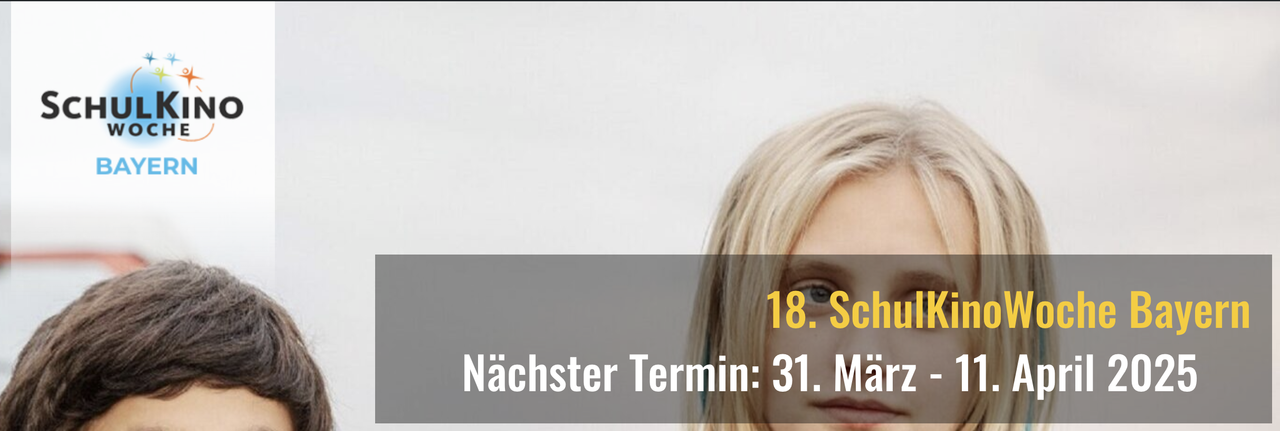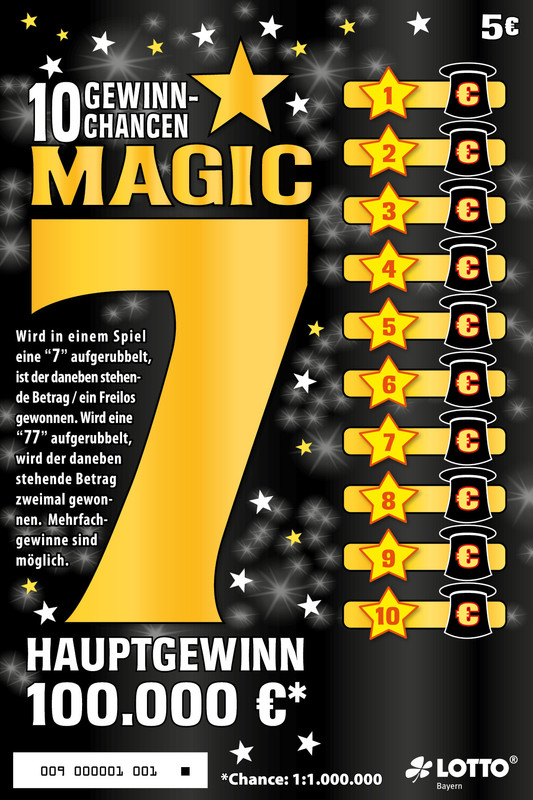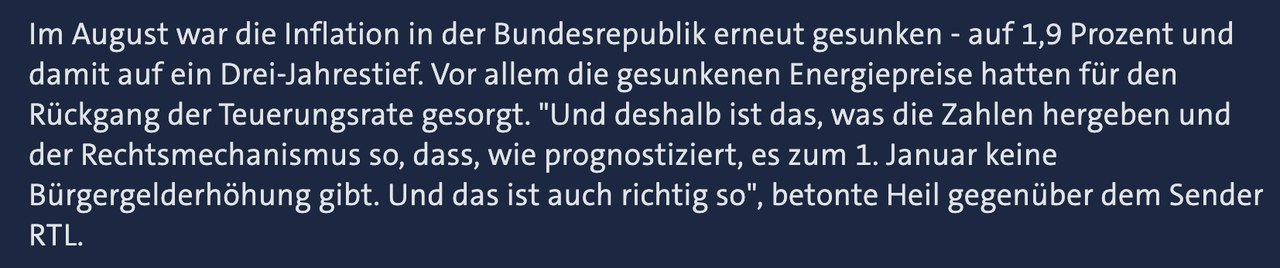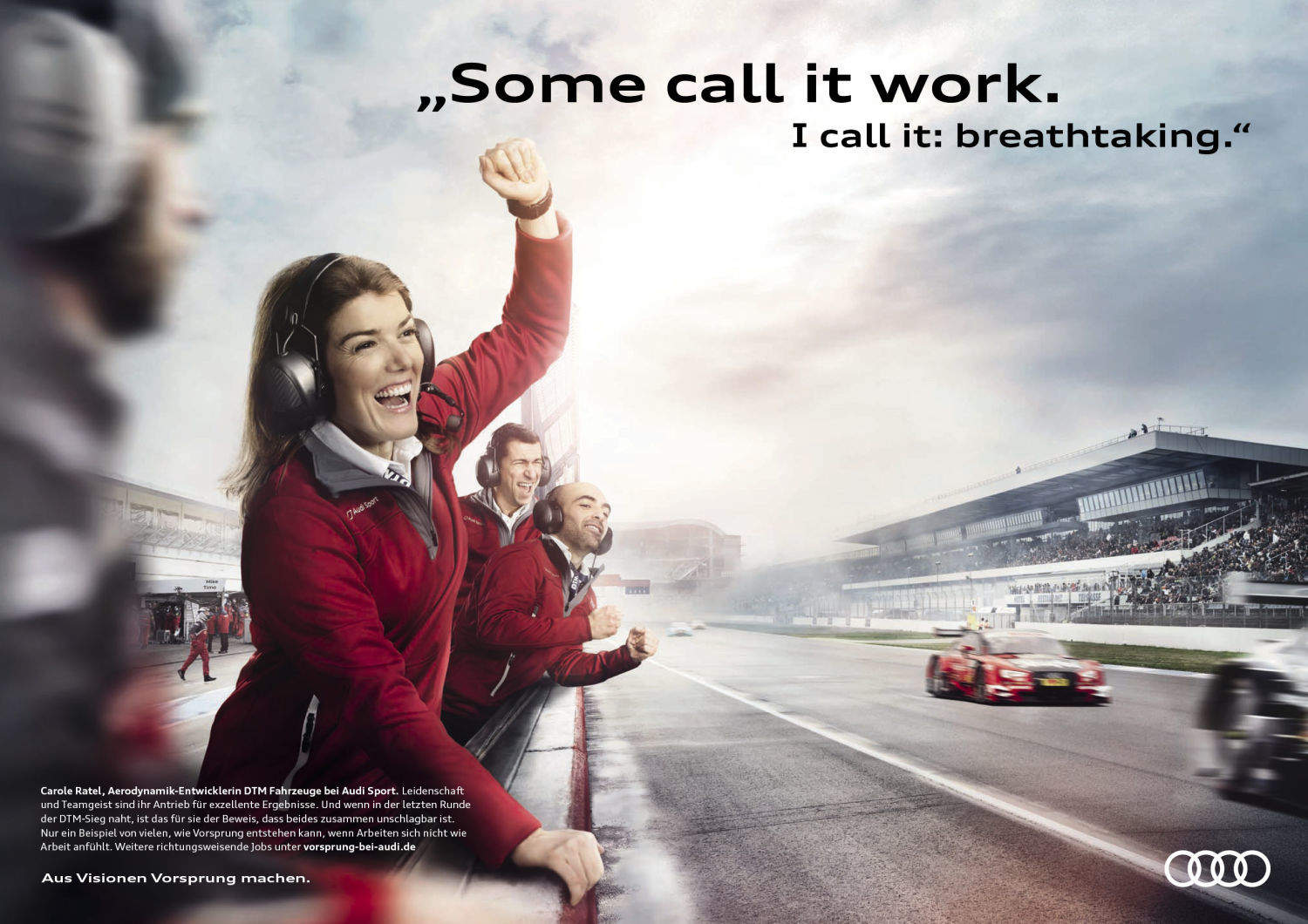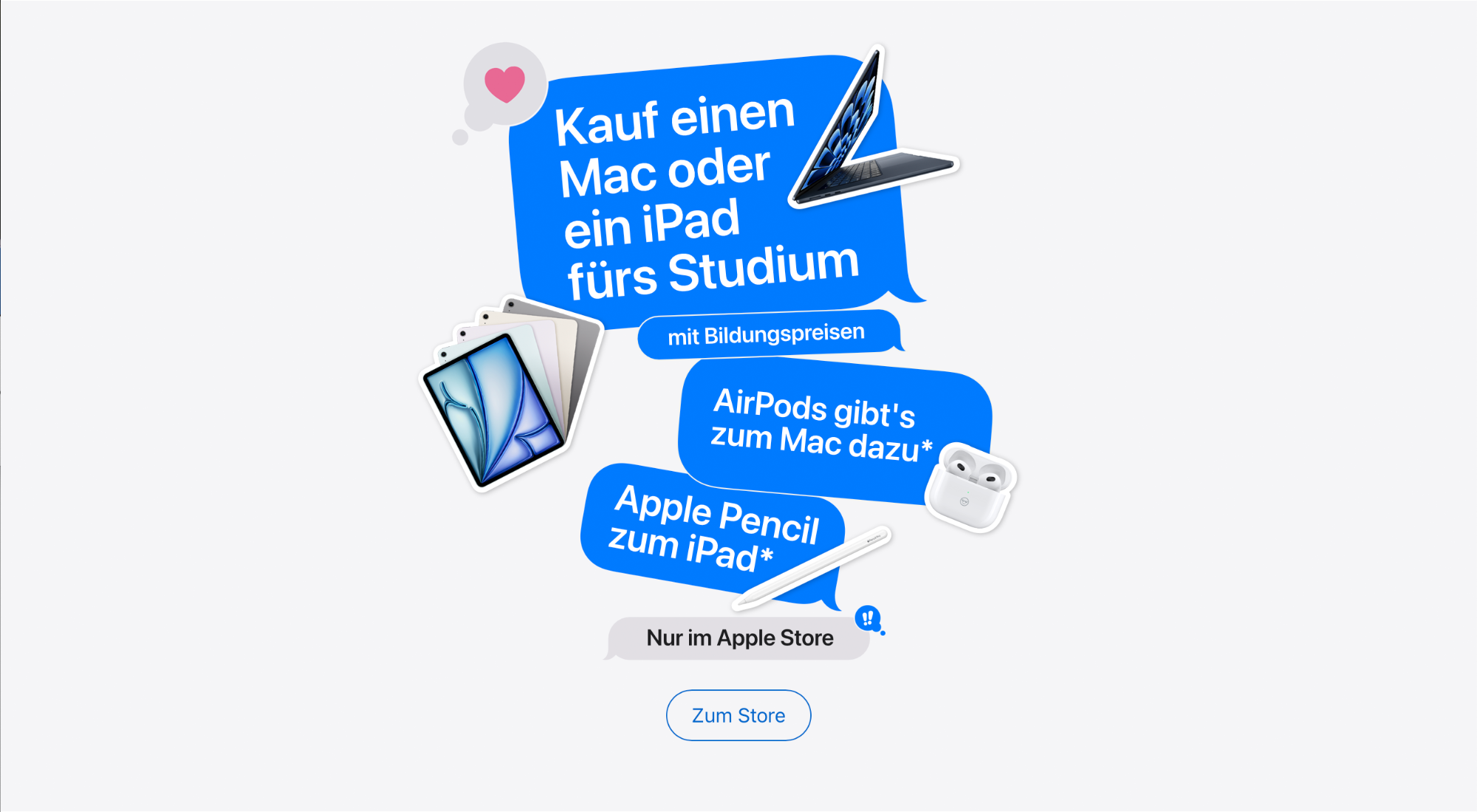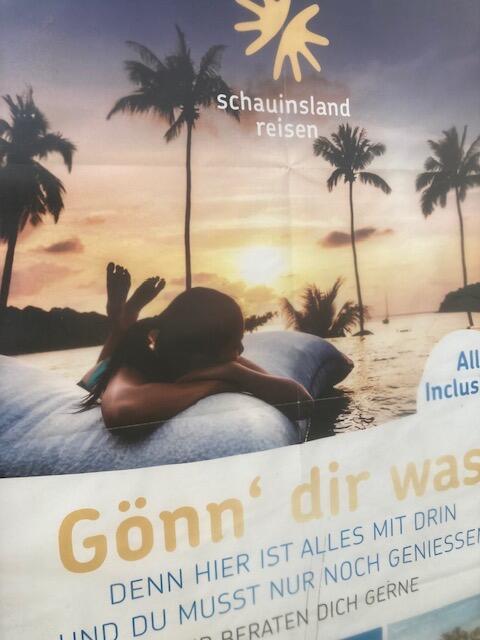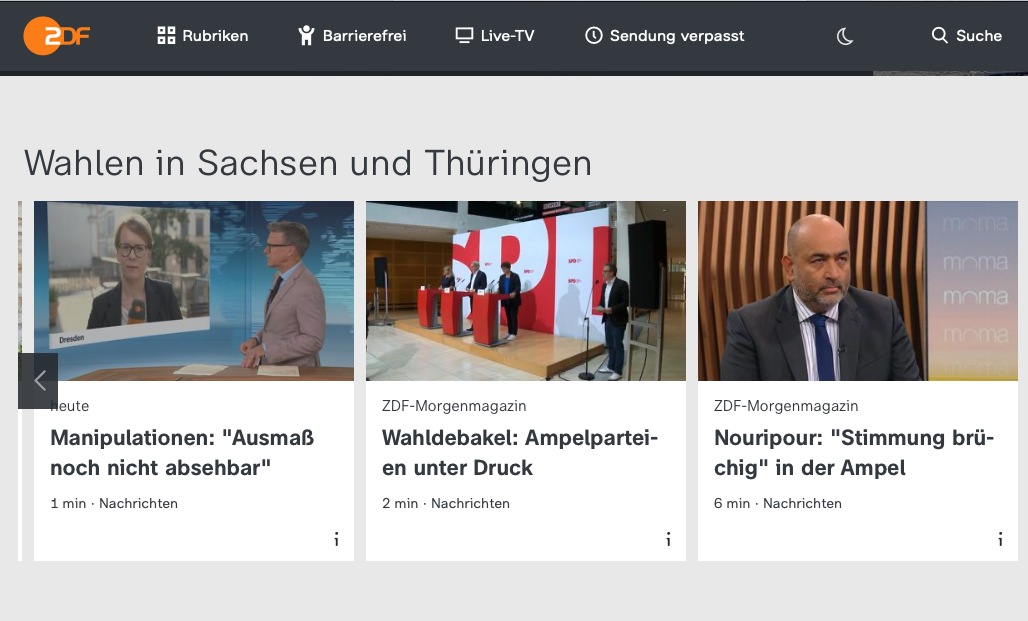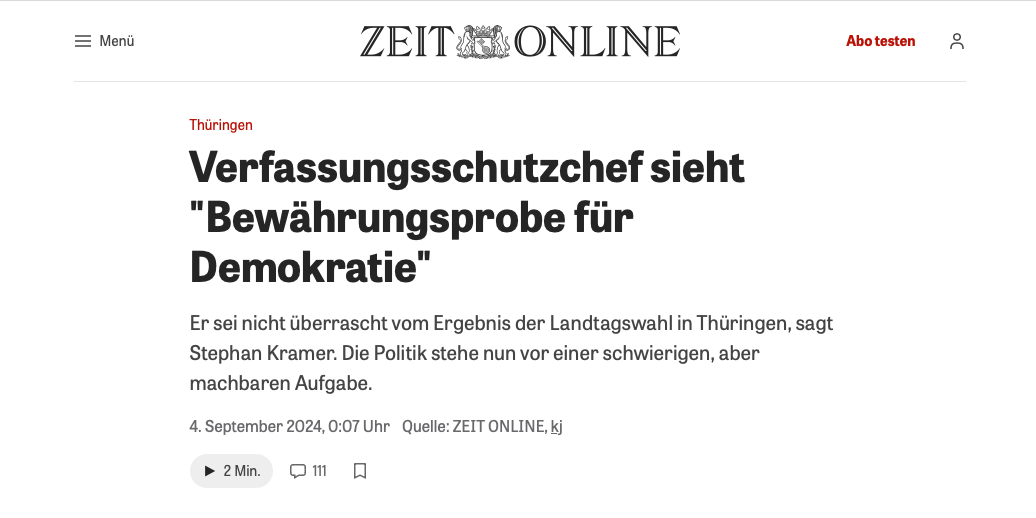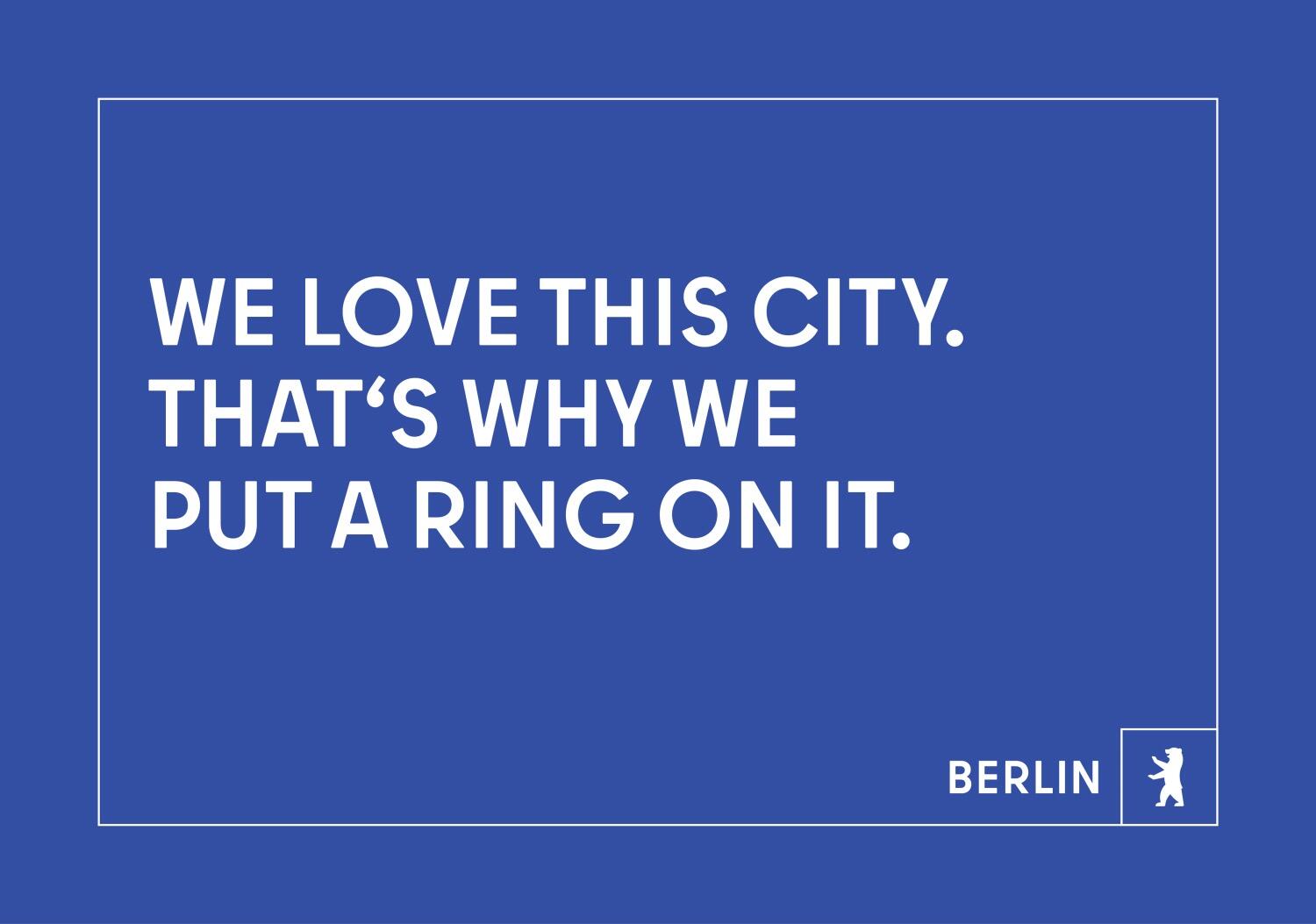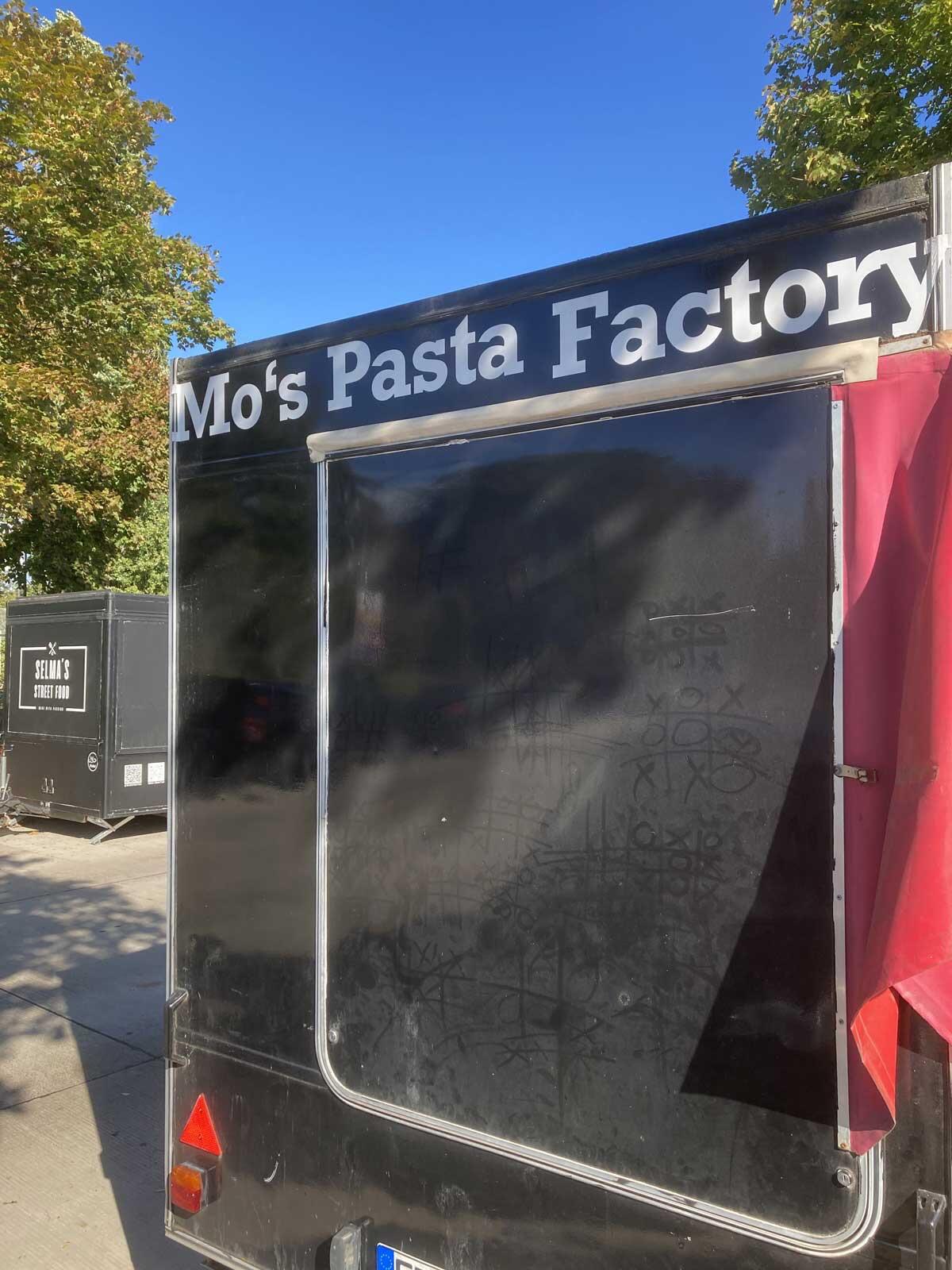
Prominente Beispiele falscher Zeichensetzung
Ich suche prominente Beispiele von Schreibmaschinen-Typografie ("" statt „“, Bindestrich statt Gedankenstrich und ähnliches) oder falschen Smart-Quotes-Ersetzungen (wie Kaiser‘s statt Kaiser’s).
Man sieht das natürlich ständig (erstrecht im Internet), aber ich suche insbesondere Beispiele, bei denen es erstens besonders markant ist (z. B. in einer kurzen Überschrift) und zweitens, bei denen man eigentlich eine anspruchsvolle Typografie erwarten würde. Also eher so Mercedes-Benz-Anzeige statt bloß YouTube-Vorschaubild
Hat jemand was parat? Ist schwer gezielt danach zu suchen.
Alle Zitate auf hessenschau.de mit "" statt „“
Beispielseite 1:
"Der Name ist Programm", sagt der Kurator Christian Kaufmann.
"Von der einen Seite sieht es so aus und wenn du weiter läufst, verändert sich es wieder. Am Schluss merkst du, du musst das so hinnehmen, wie es ist", sagt Hüter.
Beispielseite 2:
Von Debschitz, der die Strategie- und Kreativagentur Q in Wiesbaden gegründet hat und seitdem leitet, sei ein "erfolgreicher Wiesbadener Unternehmer und international anerkannter Gestalter", betonten die Kreisvorsitzenden beider Parteien, Ingmar Jung (CDU) und Christian Diers (FDP).
Schon ein paar Jahre alt …
Vielleicht ein Grenzfall. Da es eine deutsche Publikation und deutscher Copytext ist, wären die deutschen Anführungszeichen theoretisch schon richtig. Bei so wenig Text und einer optisch derart abgesetzten Headline würde ich trotzdem zu englischen Anführungszeichen greifen, zumal die Headlinemechanik über alle Motive der Kampagne identisch ist und nicht der Nationalität der jeweils abgebildeten Hauptperson zugeordnet werden kann.